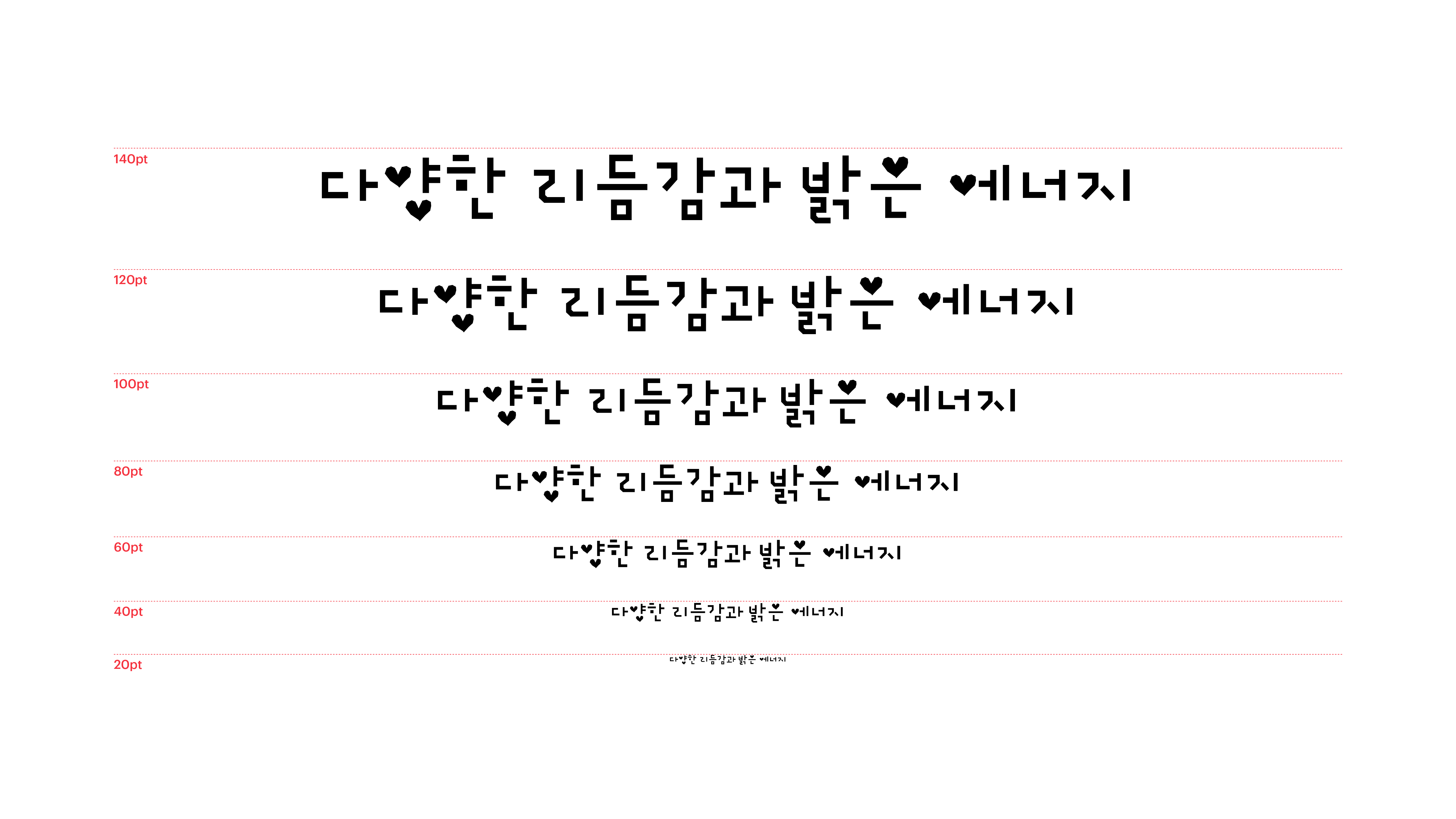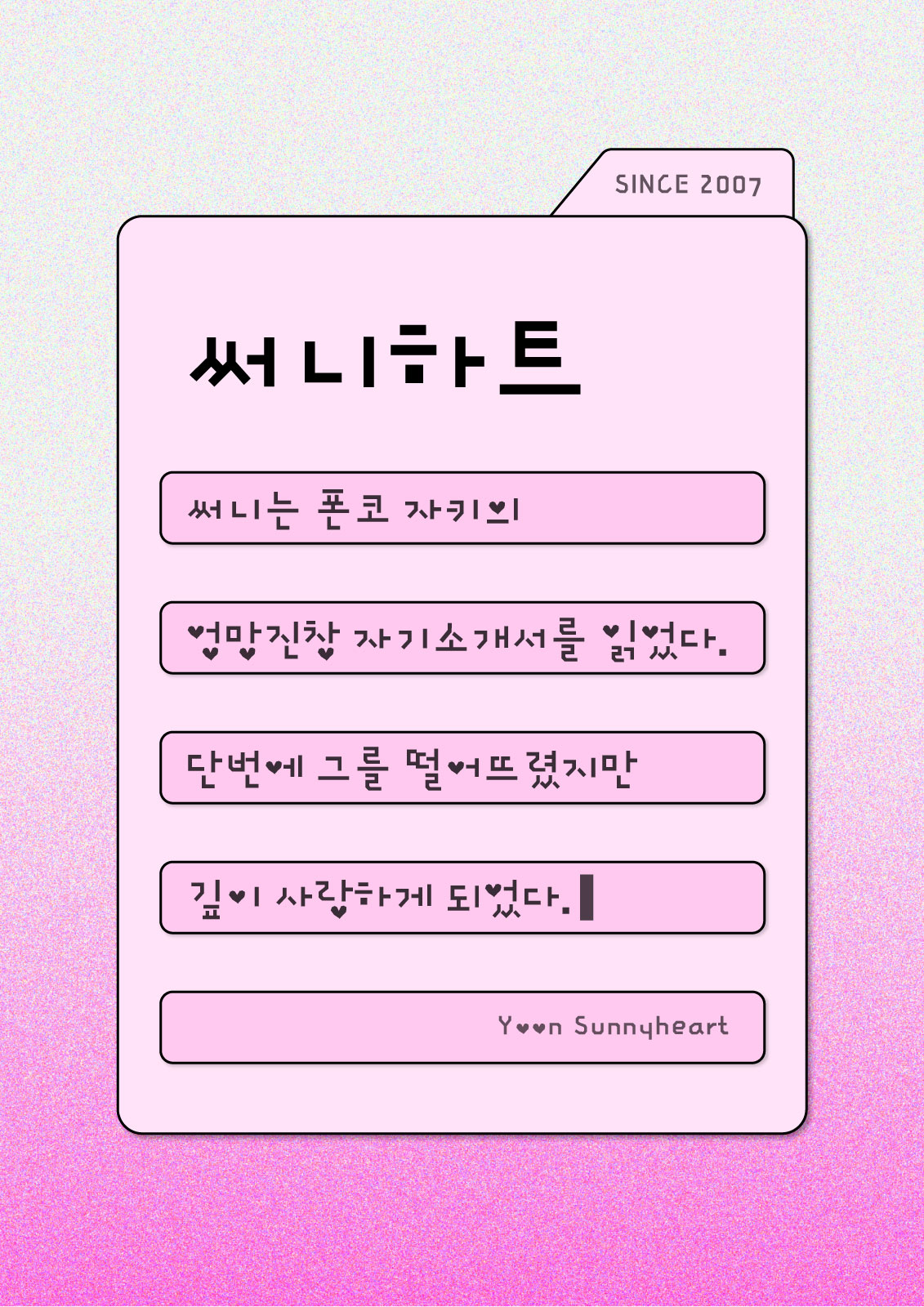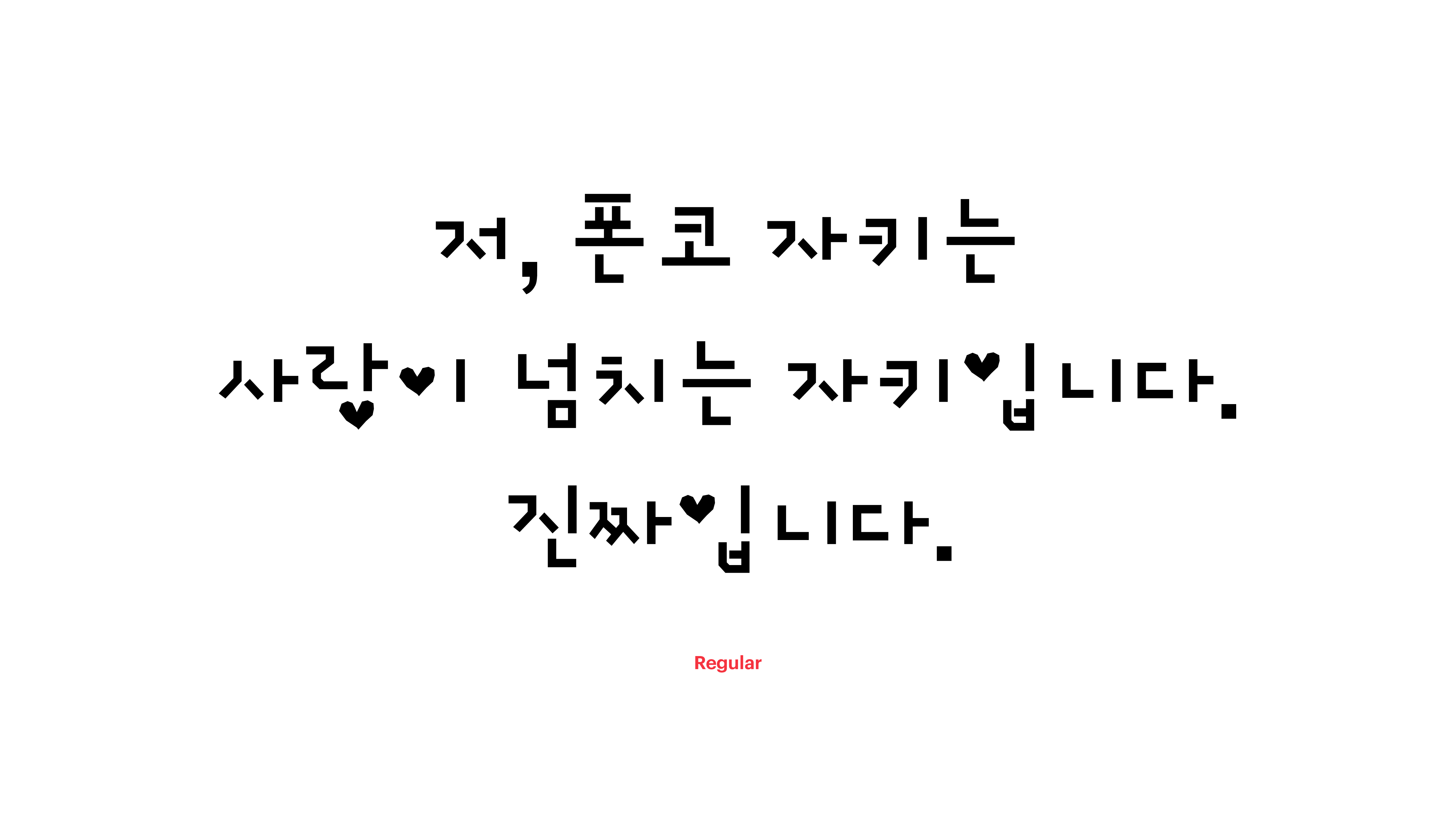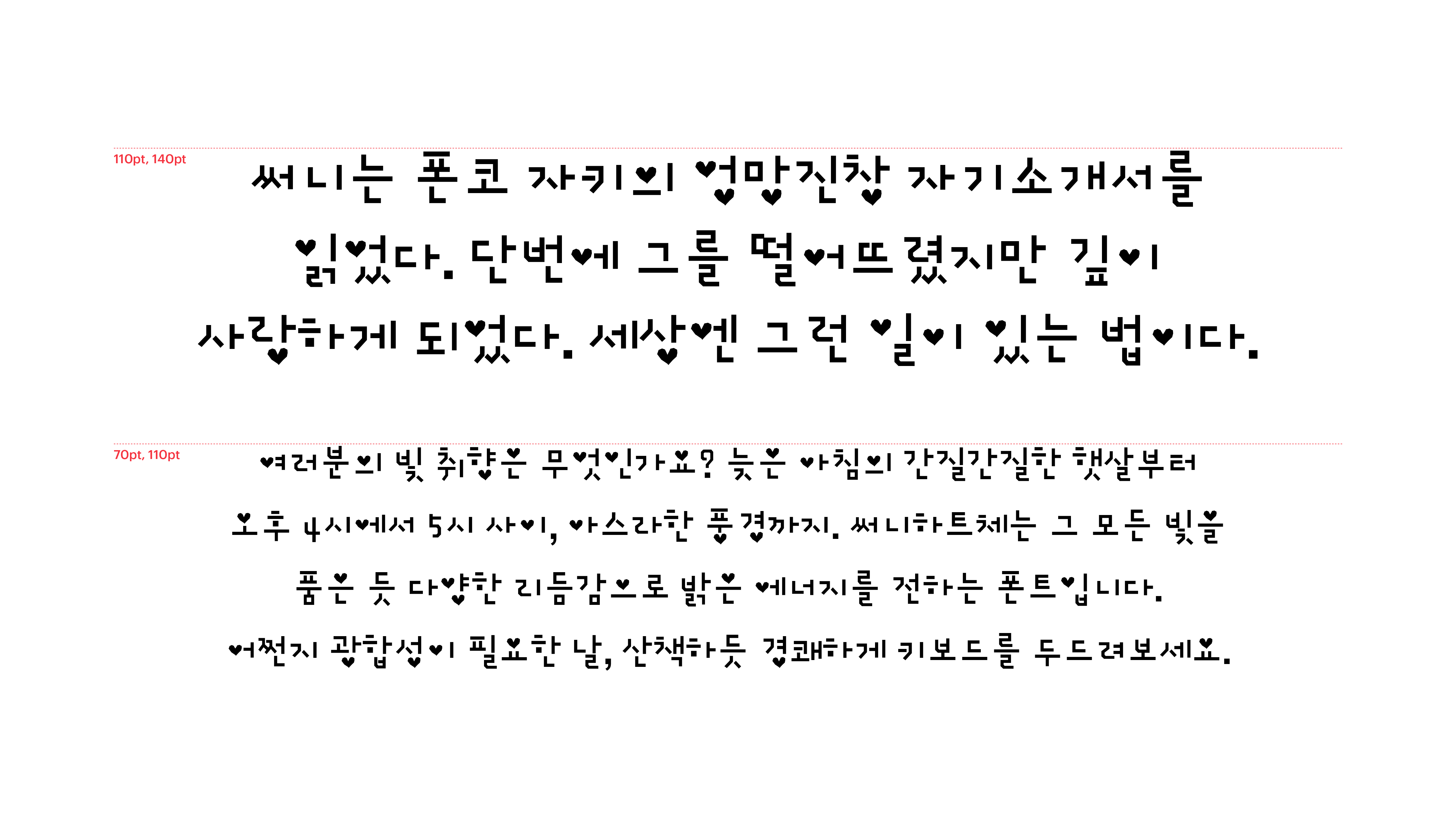
써니하트
Yoon 써니하트
여러분의 빛 취향은 무엇인가요? 늦은 아침의 발랄한 햇살부터 오후 4시에서 5시 사이, 아스라한 풍경까지. 써니하트체는 그 모든 빛을 품은 듯 다양한 리듬감으로 밝은 에너지를 전하는 폰트입니다. 어쩐지 광합성이 필요한 날, 산책하듯 경쾌하게 키보드를 두드려보세요.